面向企业主的 10 大 Adobe 字体:如何为您的品牌选择合适的字体
已发表: 2023-03-02选择正确的字体可以成就或破坏您的品牌形象。 您选择的版式会影响您的受众对您的业务的看法,并影响他们对您的内容的情绪反应。 这就是 Adobe Fonts 的用武之地。它提供了广泛的字体集合来提升您品牌的视觉识别度。 以下是用于品牌推广的 10 大 Adobe 字体列表:
1. Neue Haas Grotesk
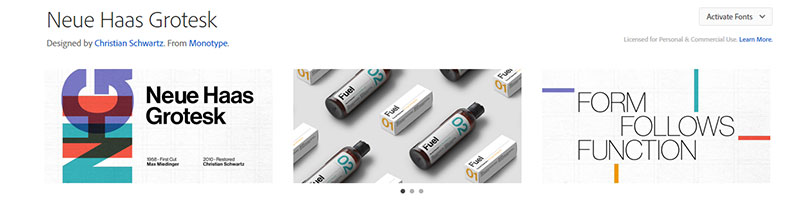
Neue Haas Grotesk 通常被称为 Helvetica,是一种永恒的多功能字体,几十年来一直受到设计师和企业主的欢迎。 它是一种出色的 Adobe 品牌字体的原因之一是它的简洁明了。 其简洁的线条和平衡的比例使其即使在小尺寸时也清晰易读,是徽标、标题和正文的理想选择。
Helvetica 的中性外观使其易于与其他字体配对,使您能够为您的品牌创建具有凝聚力和专业性的视觉标识。 有 40 多种不同的重量和款式,您可以轻松找到与您的品牌个性和信息相匹配的版本。
2.未来PT
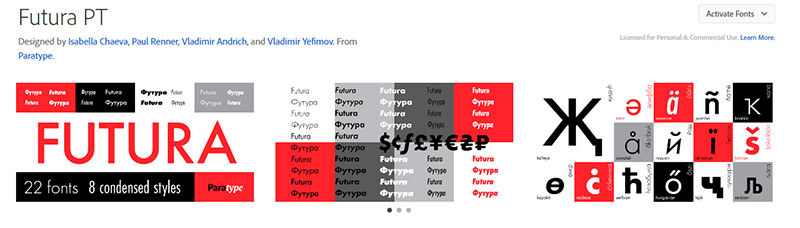
无论是品牌推广还是任何其他设计项目,Futura PT 都是您图形设计工具库中需要的 Adobe 字体。 它是一种几何无衬线字体,散发着现代感和精致感。 其简洁明了的线条传达出一种清晰和极简主义的感觉,这在现代品牌中备受追捧。 凭借其高窄的比例,Futura 在大小尺寸上也非常清晰,非常适合徽标、标题和正文。
使用 Futura 的另一个优势是它的多功能性。 除此之外,Futura 还具有永恒的吸引力、优雅和易读性,对于任何希望打造现代且独特的视觉识别的品牌来说,它都是绝佳的选择。
3. 比克汉姆剧本
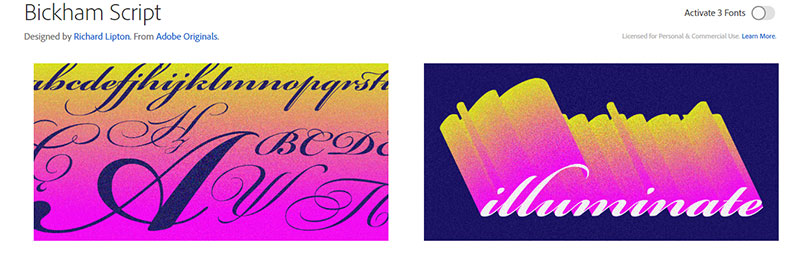
如果您正在寻找一种美丽优雅的字体,散发出精致和奢华的感觉,那么 Bickham Script 就是您所需要的。 其流畅的草书风格让人联想到传统书法,可以营造出一种旧世界的工艺感和对细节的关注。 Bickham Script 凭借其华丽而复杂的字体,特别适合旨在唤起排他性和精致感的奢侈品牌。
尽管外观华丽,但它可以用于各种上下文,从徽标和标题到正文。 它的易读性和清晰度使其易于阅读,即使是较小的尺寸。
4.小黄人
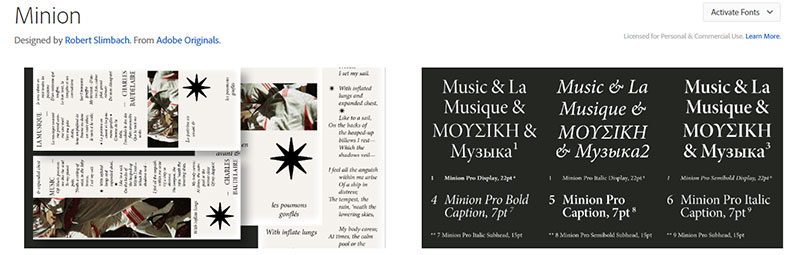
另一种 Adobe 字体非常适合那些寻找经典线条的人,Minion 散发出精致和优雅的感觉。 其平衡且成比例的字体表现出传统工艺感和对细节的关注。 如果您想建立品牌在质量和精致方面的声誉,这将特别有用。
Minion 具有清晰明确的字体,使其真正具有可扩展性,有助于确保您的品牌信息得到有效传达。 其经典而永恒的外观使其成为想要建立持久且经久不衰的视觉识别的品牌的安全可靠选择。
5. 加拉蒙高级
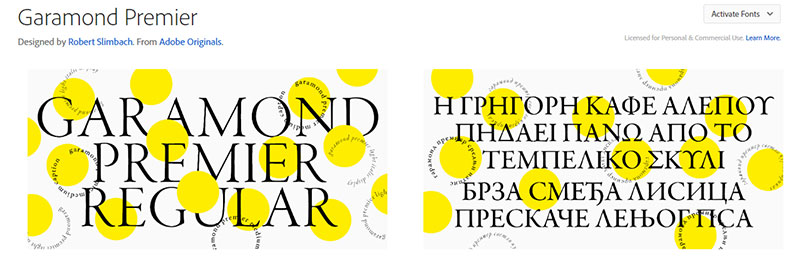
此列表中最古老的字体之一 Garamond Premier 已在印刷中使用了几个世纪。 其精致的字体散发出传统主义和工艺的气息,有助于打造高品质和优雅的品牌形象。 Garamond Premier 字体系列给人一种个性和个性的感觉。
这个特点非常适合让您的企业在竞争中脱颖而出,笔画宽度和书法繁荣的微妙变化。 如果您想营造一种传统感和传承感,这就是适合您的 Adobe 字体。
6.无数
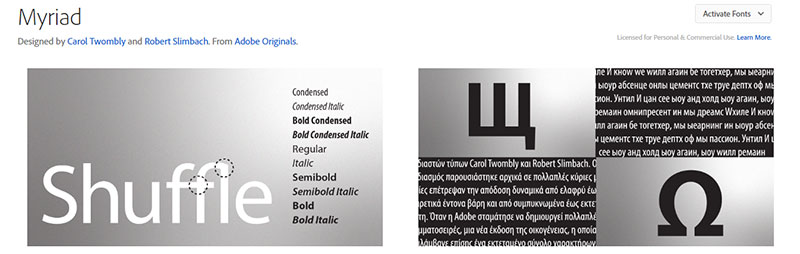
另一个优秀的 Adobe 品牌字体选择是 Myriad。 由于其现代而干净的外观以及简单而整洁的字体,它为您的品牌提供清晰和专业的服务。 此外,它具有中性而不引人注目的外观,使其成为许多品牌安全可靠的选择。
如果你想建立一个现代和专业的视觉识别而不是太大胆或华而不实,Myriad 是你需要的字体。 它的多功能性、易读性和现代魅力使其成为任何希望建立干净和现代视觉识别的品牌的绝佳选择。
7.图拉真
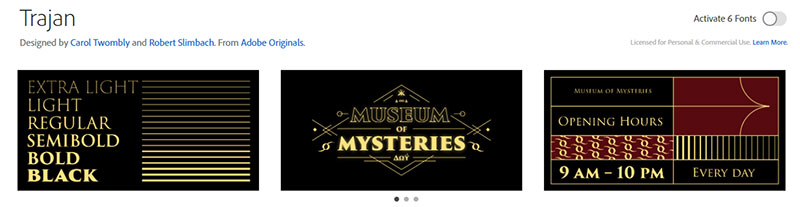
Trajan 已在平面设计中使用多年,是用于品牌推广的绝佳 Adobe 字体选择。 它有大胆和气势磅礴的字体,很好地表达了权力和权威。 如果显示力量和可靠性对您的品牌来说是最重要的,那么这就是您打造品牌所需的字体。
Trajan 具有易读性和清晰度,即使在较小的尺寸下也易于阅读。 此外,如果您想建立经久不衰的视觉识别,它经典而永恒的外观使其成为可靠的选择。
8.博多尼
Bodoni 是一种著名的经典衬线字体,对于任何旨在创建经典和永恒的品牌标识的企业来说都是一个不错的选择。 其优美的字体和有力的线条散发出精致和优雅的气息,使其成为那些希望给人留下持久印象的人的绝佳字体。
尽管它的外观有些吓人,但 Bodoni 可用于各种上下文,从徽标和标题到正文。 这也是在可扩展性方面排名很高的字体的一个很好的例子,因为无论大小如何,它看起来仍然很好。 对于希望创造持久且经久不衰的视觉识别的品牌而言,其传统而永恒的设计使其成为可靠的选择。
9.比邻星新星
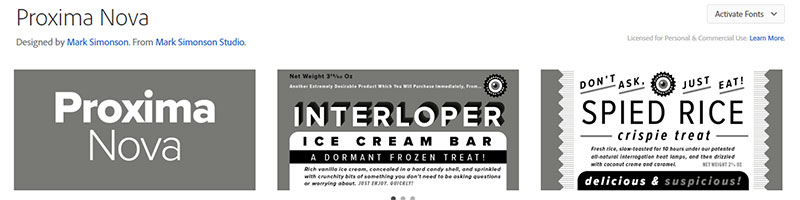
另一种非常流行的 Adobe 字体 Proxima Nova 是一种多功能的无衬线字体,是品牌推广的绝佳选择。 其几何设计赋予其现代感,可帮助您的品牌在拥挤的市场中脱颖而出。 这种字体用途广泛,可以在各种上下文中使用,例如徽标、标题和正文,而不会牺牲其易读性或清晰度。
Proxima Nova 提供各种重量和款式,让您轻松找到适合您品牌需求的完美变体。
10. Linotype Didot
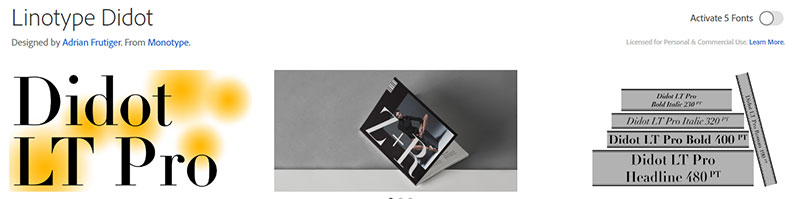
Linotype Didot 是一种散发着经典和精致感觉的衬线字体,可以帮助任何品牌建立奢华和精致的感觉。 其纤细细腻的笔触和锋利的衬线赋予其独特且可识别的外观,可以帮助您的品牌实现差异化。
Linotype Didot 清晰易读的设计,结合其经典风格,使其成为可用于一系列品牌应用的多功能字体。 此外,它具有各种重量和样式,可以轻松根据您的品牌需求进行定制。
最后的想法